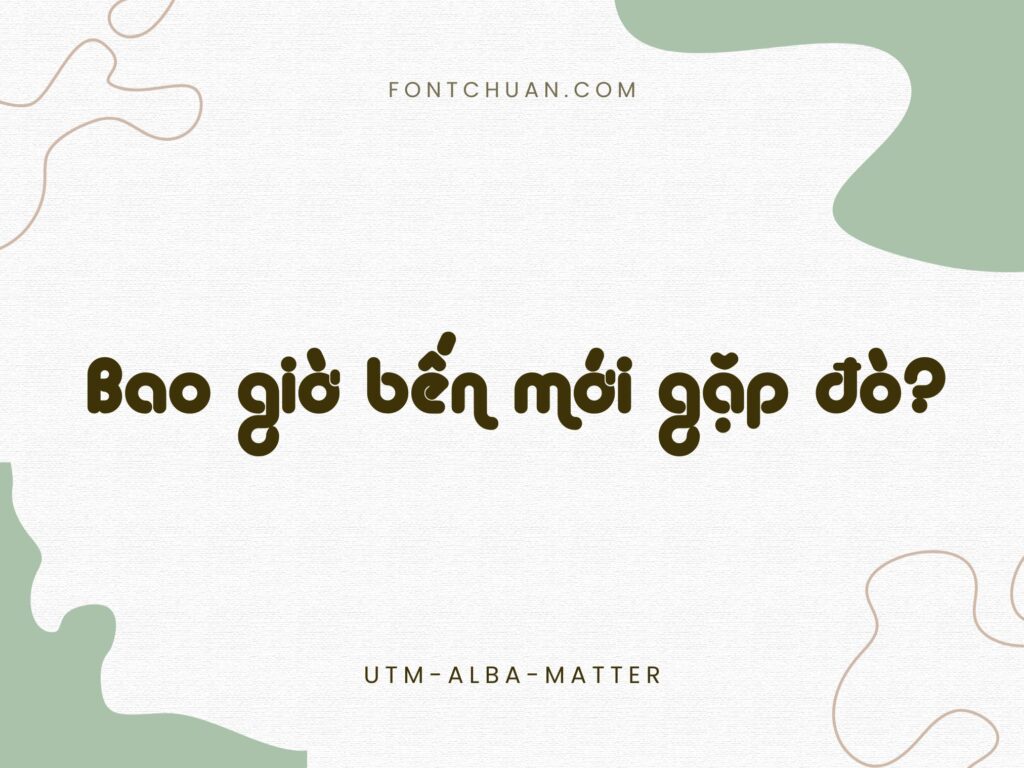
Alba Matter là một kiểu chữ sans-serif bo tròn thân thiện, được thiết kế bởi Font-a-licious Fonts và phát hành lần đầu vào năm 2001. Font mang phong cách vui tươi, hiện đại, rất phù hợp với các thiết kế mang tính trẻ trung và năng động. Phiên bản Việt hóa được thực hiện bởi Đinh Kiên, hỗ trợ đầy đủ tiếng Việt cùng hơn 100 ngôn ngữ khác. Font này đã được thành viên Font Chuẩn sưu tầm và chọn lọc nhằm phục vụ cộng đồng thiết kế trong việc tìm kiếm những giải pháp chữ hiện đại, dễ ứng dụng và phù hợp với nhiều lĩnh vực.
Alba Matter nổi bật với nét chữ tròn trịa, dày đều và độ cong mượt mà, giúp tạo cảm giác thân thiện, dễ đọc và gần gũi. Font đặc biệt phù hợp trong thiết kế bao bì sản phẩm, tiêu đề, logo, đồ họa dành cho trẻ em, thiệp mời và các ấn phẩm quảng cáo sáng tạo. Những ngành nghề như giáo dục, quảng cáo, ẩm thực và thiệp cưới đều có thể ứng dụng Alba Matter để tạo điểm nhấn độc đáo và đáng nhớ trong thiết kế.